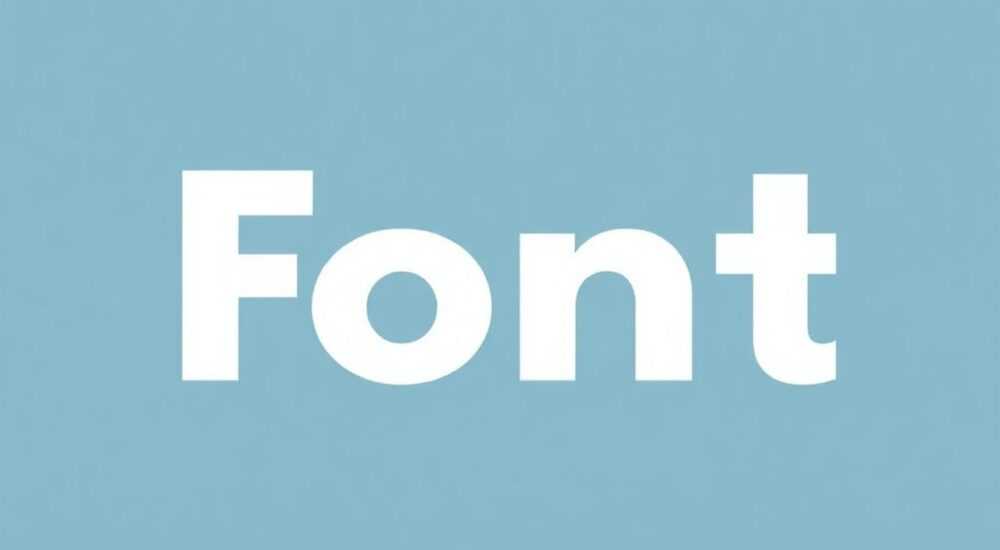
Как установить новые шрифты в фотошопе
В Photoshop шрифты — это ключевой инструмент для дизайнеров, верстальщиков и всех, кто работает с текстом визуально. Новые шрифты позволяют выразить стиль, усилить коммуникацию и подчеркнуть уникальность проекта. Однако не все пользователи знают, как правильно добавлять и активировать новые типографические решения в программе. Процесс может показаться сложным, особенно при работе с разными операционными системами или форматами файлов.
Зачем нужны новые шрифты в дизайне
Типографика — один из важнейших элементов визуальной идентичности. От выбора шрифта зависит восприятие бренда, читаемость текста и общее впечатление от макета. Штатных шрифтов, установленных в системе по умолчанию, часто недостаточно для создания уникального дизайна. Именно поэтому дизайнерам необходимо регулярно расширять свою коллекцию.
Новые шрифты помогают адаптироваться под разные задачи: от минималистичной корпоративной презентации до яркой афиши фестиваля. Каждый шрифт несёт определённую эмоцию — строгость, игривость, технологичность или роскошь. Использование правильного начертания усиливает посыл и делает работу профессиональной.
Photoshop напрямую не управляет установкой шрифтов. Он лишь отображает те, что уже доступны в операционной системе. Это означает, что процесс добавления нового шрифта начинается не в самой программе, а за её пределами — через системные настройки.
Форматы шрифтов: что выбрать и почему
Не все шрифты одинаково подходят для использования в Photoshop. Основные форматы, которые поддерживаются современными системами и программами Adobe, — это TrueType (.TTF), OpenType (.OTF) и редко — PostScript Type 1 (.PFB/.PFM). Понимание различий между ними помогает избежать проблем совместимости.
OpenType — наиболее продвинутый и рекомендуемый формат. Он поддерживает расширенные функции: альтернативные глифы, капительные цифры, стилистические наборы и множественные языковые таблицы. Это особенно важно при работе с многоязычными проектами или художественной типографикой.
TrueType — старый, но до сих пор широко используемый формат. Он хорошо работает в большинстве случаев, но лишён продвинутых возможностей OpenType. Тем не менее, для простых задач его более чем достаточно. Главное — убедиться, что шрифт корректно отображается и не вызывает ошибок.
Где скачивать шрифты безопасно
Выбор источника — критически важный этап. Установка шрифтов с сомнительных сайтов может привести к заражению системы или юридическим последствиям. Лучше использовать проверенные платформы с лицензионными шрифтами.
- Google Fonts — бесплатная коллекция с открытым лицензированием. Подходит для личных и коммерческих проектов.
- Adobe Fonts — часть подписки Creative Cloud. Интеграция с Photoshop позволяет активировать шрифты одним кликом без установки на диск.
- Dafont — обширная база, но требует внимательной проверки лицензии. Многие шрифты только для личного использования.
- Fontspring, MyFonts, Linotype — платные, но высококачественные источники с полной коммерческой лицензией.
Как установить шрифты на Windows
Windows предоставляет несколько способов установки шрифтов. Самый простой и надёжный — через встроенную панель управления шрифтами. Этот метод гарантирует, что шрифт будет доступен всем приложениям, включая Photoshop.
Первым делом найдите скаченный файл шрифта. Обычно это .TTF или .OTF. Кликните по нему дважды — откроется предварительный просмотр. В верхнем левом углу нажмите кнопку «Установить». Система скопирует файл в папку C:WindowsFonts и зарегистрирует его.
Если вы хотите установить несколько шрифтов сразу, выделите их в проводнике и нажмите правой кнопкой мыши → «Установить». Также можно вручную скопировать файлы в папку шрифтов, но первый способ предпочтительнее — он включает автоматическую проверку целостности.
Проверка установки
После установки откройте любое приложение с текстовым редактором (например, Word или Блокнот). Создайте новый документ и проверьте, появился ли нужный шрифт в выпадающем списке. Если да — он готов к использованию в Photoshop.
Как установить шрифты на macOS
macOS предлагает ещё более удобный интерфейс для работы со шрифтами — приложение «Шрифты» (Font Book). Оно позволяет не только устанавливать, но и управлять, дублировать и удалять шрифты.
Для установки дважды кликните по файлу шрифта. Запустится Font Book, где отобразится предварительный просмотр. Нажмите «Установить шрифт» — система добавит его в библиотеку пользователя. Шрифт станет доступен во всех приложениях, включая Photoshop.
Если вы работаете в команде или на нескольких устройствах, можно создавать коллекции шрифтов в Font Book. Это удобно для проектов с единым стилем. Также приложение автоматически проверяет шрифты на наличие ошибок и сообщает о конфликтах.
Использование Adobe Fonts в macOS
Если вы используете подписку Creative Cloud, лучший способ — Adobe Fonts. Зайдите на fonts.adobe.com, найдите нужный шрифт и нажмите «Активировать». Он появится в Photoshop без необходимости скачивания или установки.
Что делать, если шрифт не появился в Photoshop
Иногда, несмотря на корректную установку, шрифт не отображается в Photoshop. Причин может быть несколько: кэширование, повреждение файла, конфликт имён или отсутствие перезапуска программы.
Первое, что нужно сделать — перезапустить Photoshop. Программа загружает список шрифтов при запуске, и новые могут не попасть в текущую сессию. Если это не помогло, проверьте, действительно ли шрифт установлен в системе.
На Windows откройте «Параметры» → «Шрифты». На macOS — запустите Font Book. Убедитесь, что шрифт есть в списке и не помечен как повреждённый. Также проверьте, нет ли дубликатов — два шрифта с одинаковым названием могут вызывать конфликты.
Очистка кэша шрифтов в Photoshop
Photoshop кэширует информацию о шрифтах для ускорения работы. Чтобы сбросить кэш:
- Закройте Photoshop.
- Удерживайте Ctrl+Alt+Shift (Windows) или Cmd+Option+Shift (macOS) при запуске программы.
- Подтвердите очистку настроек (это не удалит ваши файлы).
- Запустите Photoshop заново.
Ошибки и как их избежать
Даже опытные пользователи допускают типичные ошибки при работе с шрифтами. Знание этих ловушек поможет сэкономить время и избежать разочарований.
Одна из самых частых — установка шрифтов путём копирования в папку Photoshop. Это не работает. Photoshop не считывает шрифты из своей директории. Они должны быть установлены на уровне системы.
Другая ошибка — использование шрифтов с ограничениями. Например, шрифт с лицензией «Personal Use Only» нельзя применять в коммерческих проектах. Это может привести к претензиям со стороны правообладателя.
- Не скачивайте шрифты с торрентов или неофициальных форумов.
- Проверяйте расширение файла: .exe может быть вирусом, маскирующимся под шрифт.
- Избегайте установки слишком большого количества шрифтов — это замедляет систему и затрудняет поиск нужного.
Чек-лист перед установкой
- Проверил лицензию шрифта?
- Скачал файл с надёжного источника?
- Убедился, что формат — .TTF или .OTF?
- Установил через систему, а не вручную в папку Photoshop?
- Перезапустил Photoshop после установки?
Качественная типографика начинается с правильного выбора и управления шрифтами. Лучше иметь небольшую, но хорошо организованную коллекцию, чем сотни неиспользуемых начертаний. Важно понимать, что шрифт — это не просто форма, а инструмент коммуникации.
Приоритет стоит отдавать шрифтам с хорошей читаемостью, адекватной межбуквенной коррекцией и поддержкой кириллицы, если вы работаете на русском языке. Многие популярные зарубежные шрифты имеют слабую реализацию кириллических символов.
Автоматизация — следующий уровень. Использование Adobe Fonts или менеджеров шрифтов (например, Suitcase Fusion или NexusFont) экономит время и снижает риск ошибок. Особенно это актуально при работе в команде или на нескольких компьютерах.
Установка новых шрифтов в Photoshop — это простой, но требующий внимания процесс. Главное правило: шрифт сначала устанавливается в операционную систему, а затем становится доступным в программе. Соблюдение этого порядка избавляет от большинства проблем.
- Шрифты устанавливаются через систему, а не вручную в папку Photoshop.
- Форматы .OTF и .TTF — самые надёжные и универсальные.
- Adobe Fonts и Google Fonts — безопасные и удобные источники.
- Всегда проверяйте лицензию перед использованием шрифта.
- Перезапуск Photoshop и очистка кэша решают большинство проблем с отображением.